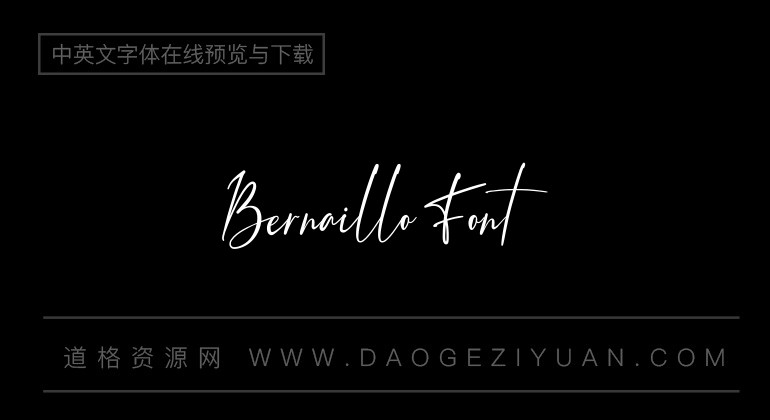
Bernaillo Font
Bernaillo字体是一种手写风格的字体,其设计灵感来源于西班牙语中的手写风格,字母间距较小,字母形状也比较圆润,给人一种亲切、温暖的感觉。这种字体适合用于卡片、海报、宣传册、手写信件等类似的设计中,可以营造出浪漫、温馨的感觉。Bernaillo字体包括大小写字母、数字、标点符号和特殊字符,支持多种语言。
Bernaillo Font是一款非常不错的手写艺术字体,具有很好的视觉感,适合于文化类的宣传设计、商业类品牌的广告和产品包装设计以及个性化文字排版等较多场景。